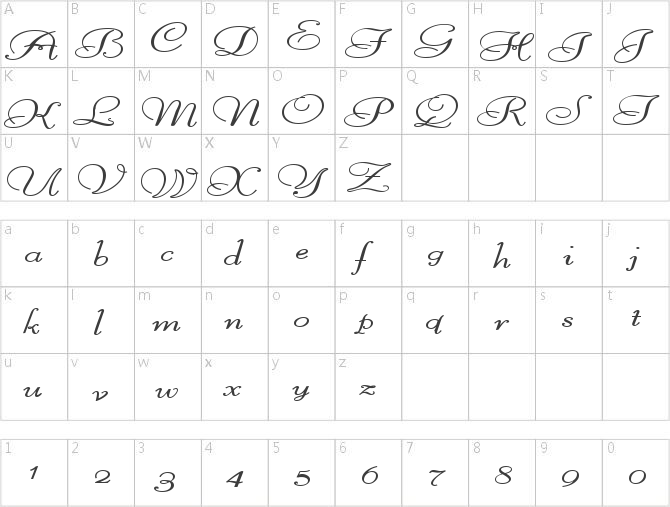
Liberate-Extended-Bold
Liberate-Extended-Bold介紹
Liberate-Extended-Bold字體字庫是一款讓人賞心悅目、百看不厭的英文字體,適合各類廣告和產品包裝設計應用,字體大小0.07MB,格式為ttf字體,上傳用戶是dqq520,作者/版權方為未知